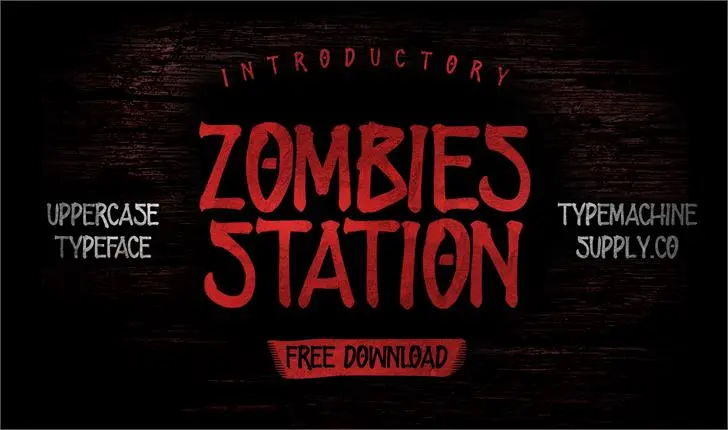
ZOMBIES STATION Font – Download Grátis
A ZOMBIES STATION Font surge como uma criação inovadora para designers que buscam uma fonte única e vibrante para seus projetos de graffiti. Especialmente adequada para grafite, esta fonte se torna um recurso valioso para qualquer designer interessado em criar peças de arte urbana memoráveis. Com traços agradavelmente grotescos e detalhes efêmeres que remetem aos elementos característicos da cultura do zumbi, ZOMBIES STATION captura o espírito desconcertante e vibrante deste movimento. Suas letras expressivas podem transformar qualquer obra em arte urbana ou graffiti em uma experiência visual impressionante, capaz de chamar a atenção das ruas mais caóticas. Ideal tanto para designers urbanos quanto para artistas digitais que buscam adicionar um elemento único e inovador aos seus projetos, ZOMBIES STATION Font é perfeita para aqueles procurando por uma fonte resistente à rotina, que enriquece suas criações com uma visão mais atraente e criativa. Não importa o tamanho ou formato de sua obra, esta fonte irá torná-la o destaque no qual você sempre sonhou.
Designer: Typemachinesupply